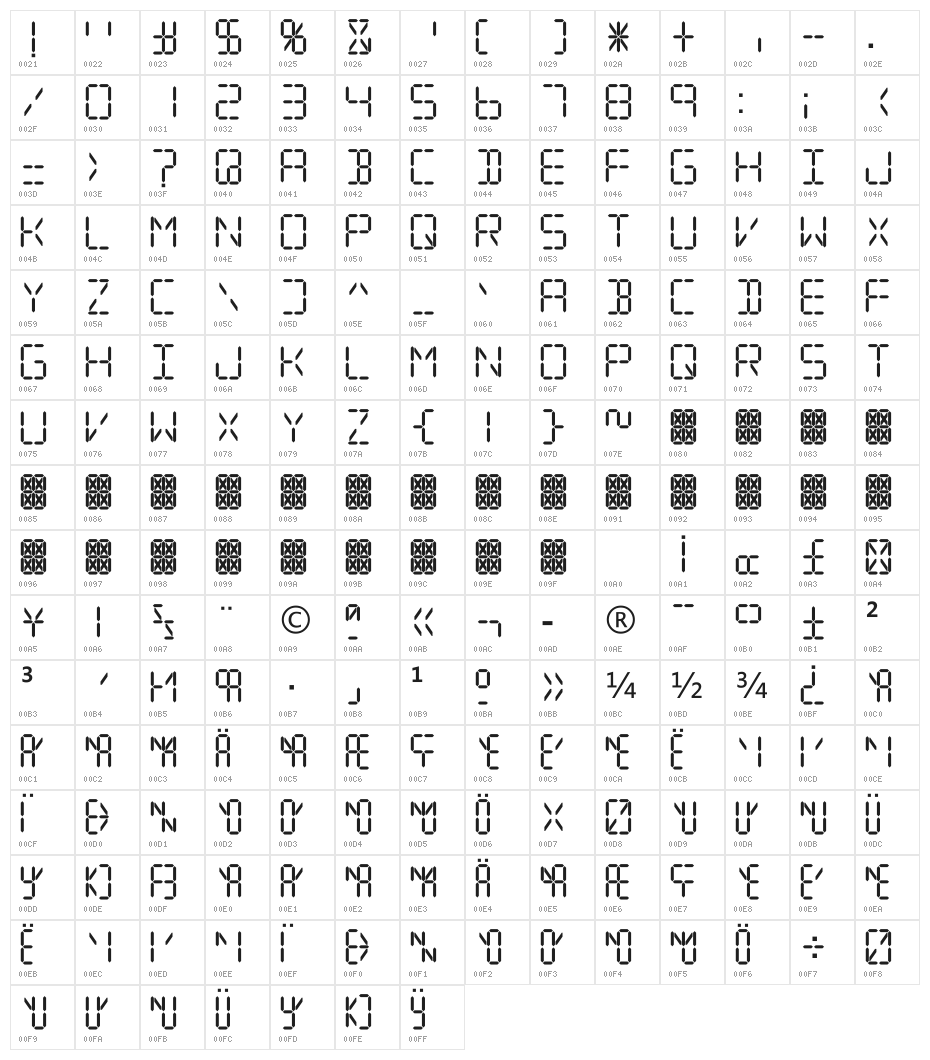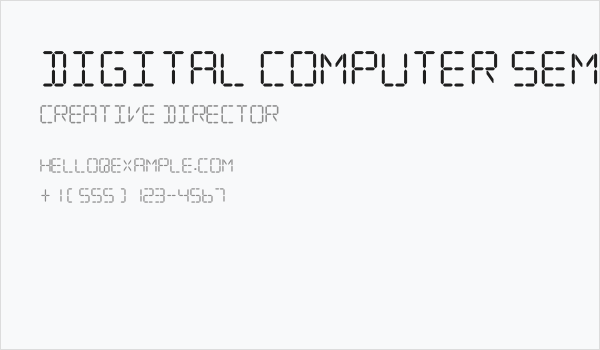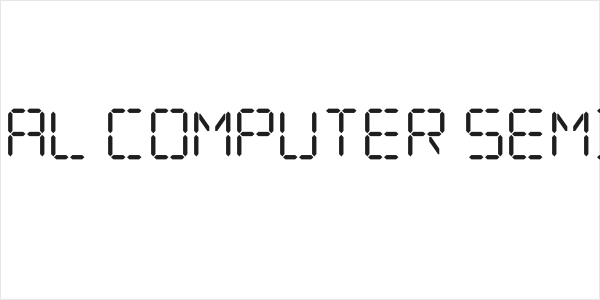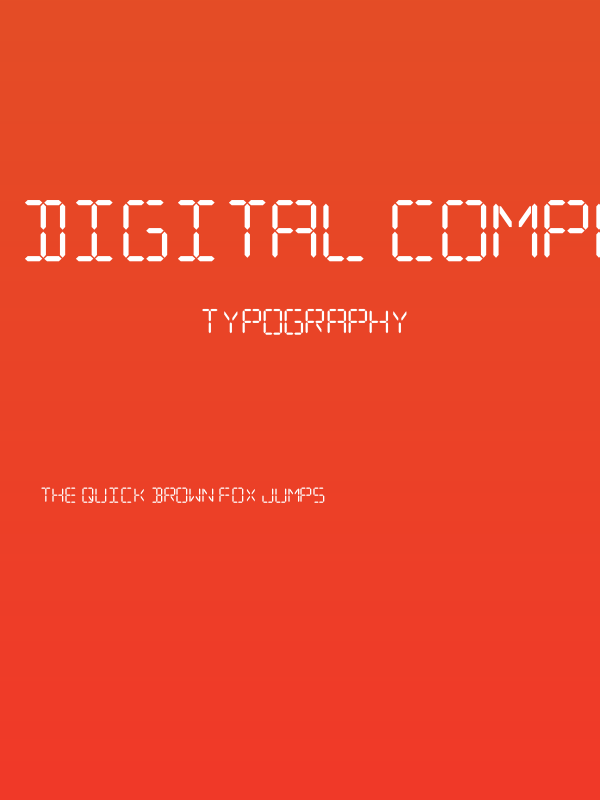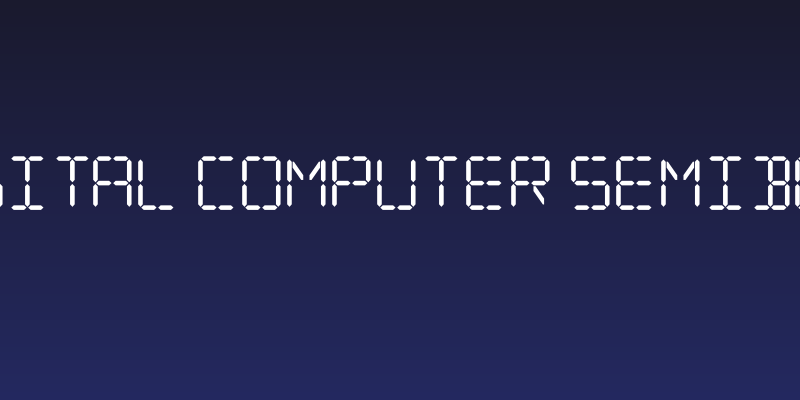
Digital Computer Semibold Font
| 使用场景 | Headlines, Digital displays, Tech interfaces |
| 推荐项目 | Ideal for digital interfaces, tech-themed designs, retro-futuristic projects, and any application requiring a digital or technical aesthetic. |